Benny曾因這堵牆上的鸚鵡而造了個「唱」字,但當日我們去到車房,老闆說愛雀已仙遊,一對鸚鵡只剩下一隻,難免令人欷歔。
作為本地著名的平面設計師,區德誠(Benny)是個字戀狂。近年他相機不離身,從街頭巷尾捕捉到的光影,原來都是為他所愛戀的漢字尋找當下的意義,喚醒久經電腦時代壓抑而沉睡的漢字生命,每個經他再造的字,一如香港,既有着傳統美學標準,但更有的是在這個時空的全新演繹。一如倉頡造字,Benny 的字是由象形出發再賦予他從這城接受到的各種情感,因此他的字,讓漢字重奪一字一世界的魔法。
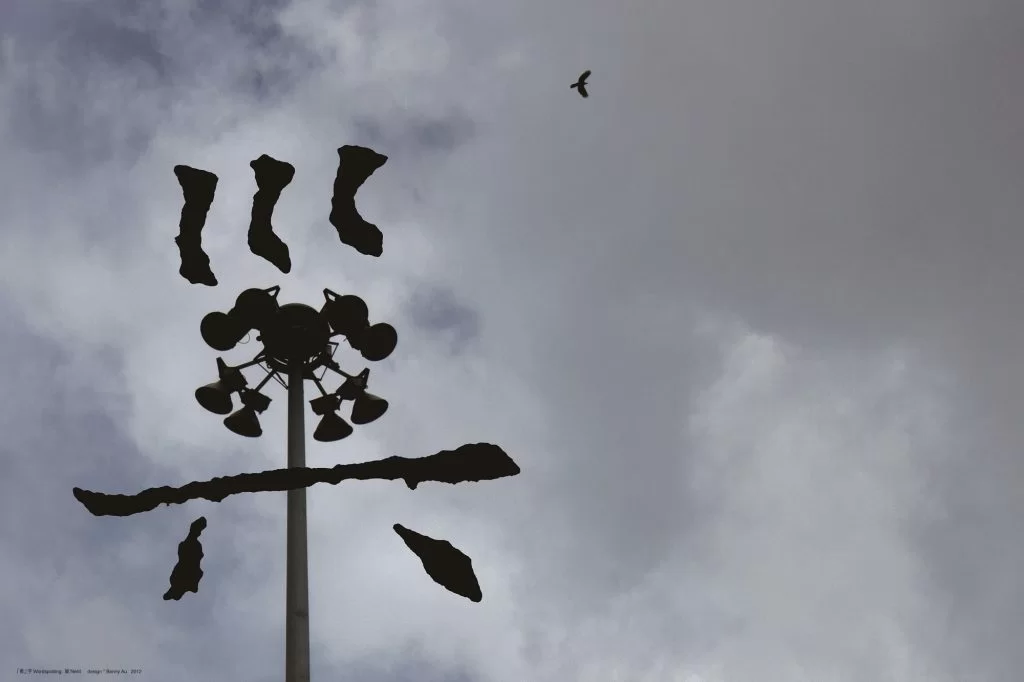
一天在紅磡等車,抬頭看見燈杆上三兩隻海鵰盤旋,原來上有鳥巢一個,思緒便從現實釋放出來。回到公司後,Benny 從古字帖中找來適用模件砌「巢」字,來說明了現代城市雀鳥的居住生態。
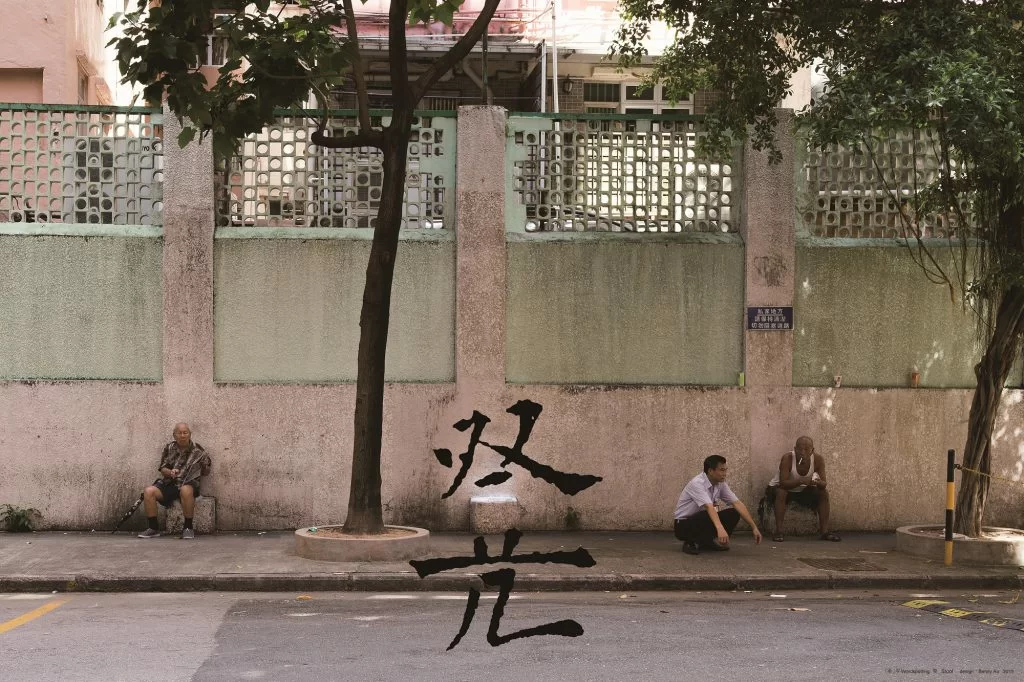
本來只是一堵牆下一嚿嚿突出的牆腳結構裝飾(?),因為被人發現了「凳」的功能而成為叔伯們的私家位,Benny 在此只不過立此存照,有碟話碟,但觀者無不感受到那份久違了悠閒。
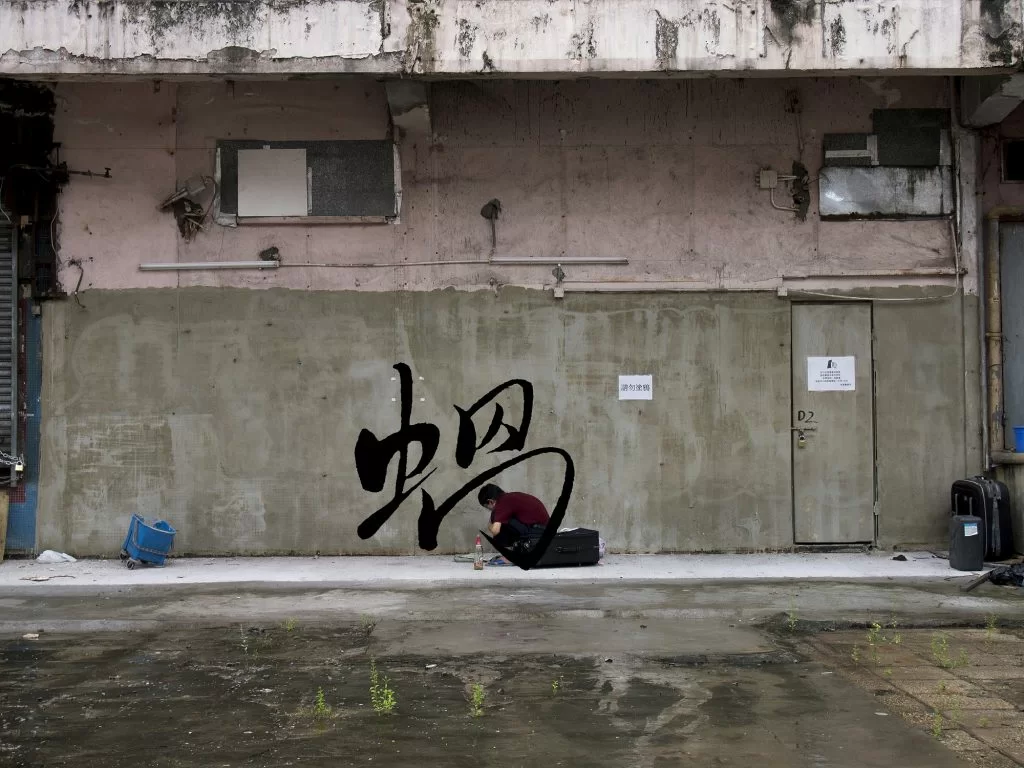
香港的土地問題和貧富懸殊有幾嚴峻,都在這張相以露宿者和他全副家當作為拍攝對象的「蝸」字中,表現無遺。
Benny 說,「古人造字按『六書』,象形、指事、會意、形聲、轉注和假借。我造字,想的是讓漢字找回浪漫性。
很多人造字,抱着不同目的:商業化設計化形式化或功能性。這樣造出來的字,相對藝術性很少。但漢字是一種感性很強的文字,每個字本身都有其意思有其故事,不像英文字母是一些讀音,本身沒有意義。因此漢字先天便是一種具有藝術氣質的文字─當我們說藝術和設計,說的是針對精神層面和視覺/肉體層面,兩種截然不同的愉悅。我們身處電腦時代,針對視覺肉體層面的愉悅相對易得,而精神層面的愉悅,卻不單單從表面漂亮而獲得,而是要從情感交流而來的,太過工整太過統一,就會磨平了藝術性。所以我造字,是從生活中觀察,當捕捉了一個有趣的畫面,然後要找到跟畫面氣氛韻味相配的古字,一今一古的圖像和文字模件結合,為的是想表現那個字在今天我們生活中的意義,有時我要看遍同一書法家,將兩個字拼合才找到我想從整個畫面呈現的意義/故事。通常我是先有對某個字的想法,然後才出去尋找拍攝對象,或找找尋合適的氣氛。但有時路上碰巧遇上難得剎那,亦會馬上拍下然後才回來找合用古字部分拼合。」